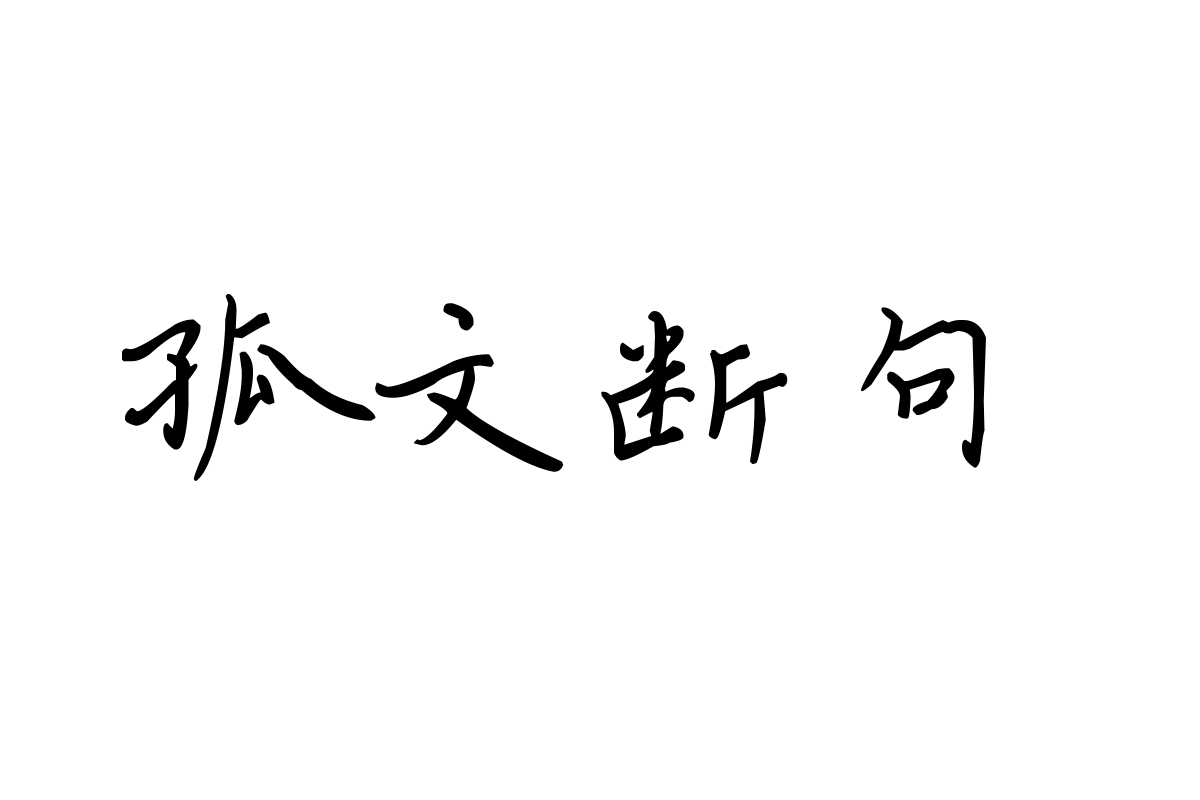
米开簪花小楷是一种特殊的书法字体,它源自于唐代书法家米芾的“簪花小楷”。这种字体的特点是笔画流畅,结构严谨,字形秀美。它的书写速度相对较快,但每个字的笔画都非常清晰,给人一种优雅的感觉。
米开簪花小楷的笔画特点是:线条流畅,结构紧凑,字形秀美。它的笔画粗细适中,既有力度又不失柔美,使得整个字体看起来既庄重又典雅。此外,这种字体还注重笔锋的变化,使得每个字都充满了生命力和动感。
总的来说,米开簪花小楷是一种非常独特而优美的字体,它不仅具有很高的艺术价值,也深受广大书法爱好者的喜爱。